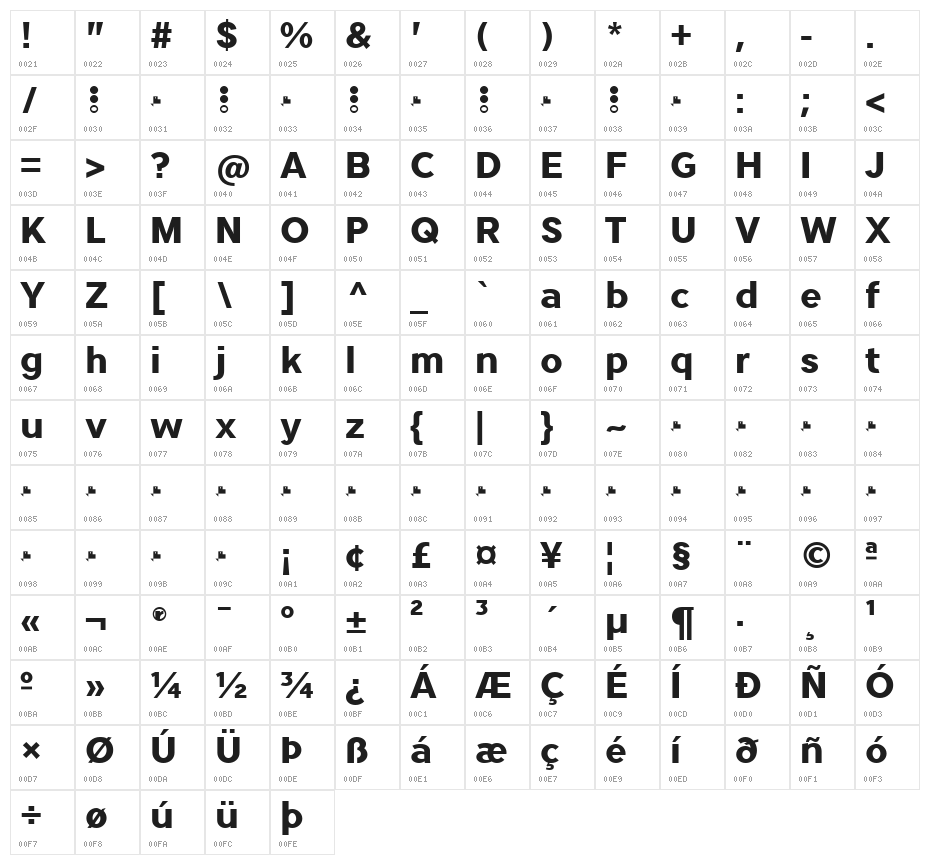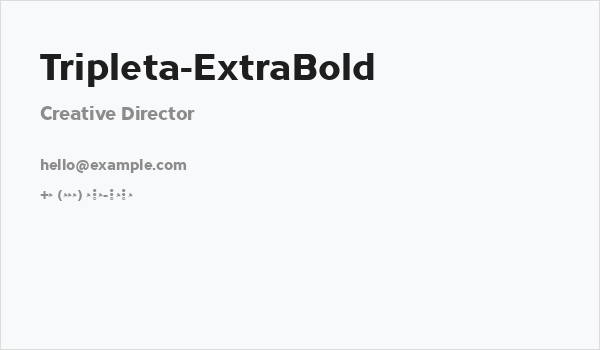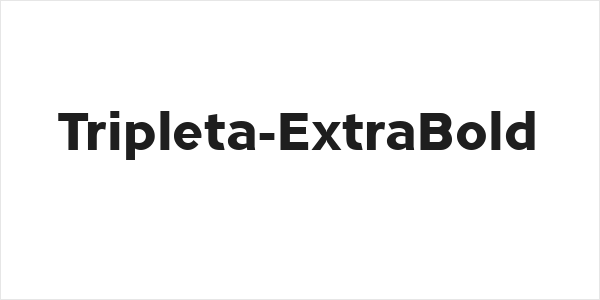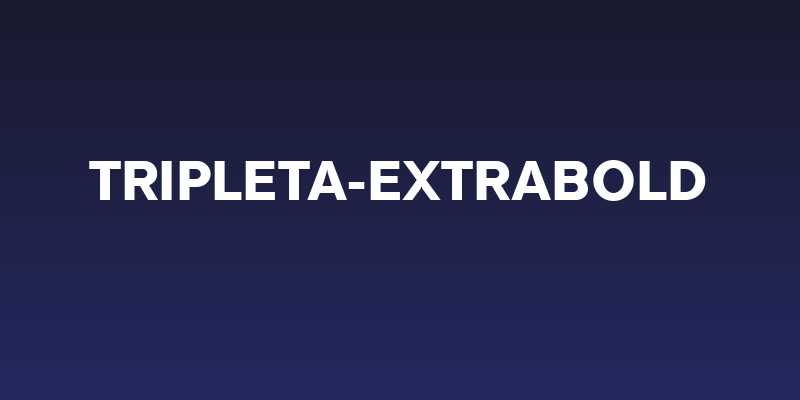
Tripleta-ExtraBold Font
✎ Round
| 分类 | Round |
| 使用场景 | Headlines, Logos, Branding |
| 推荐项目 | This font is perfect for branding projects, advertising campaigns, poster designs, and digital media where a strong, modern presence is needed. |